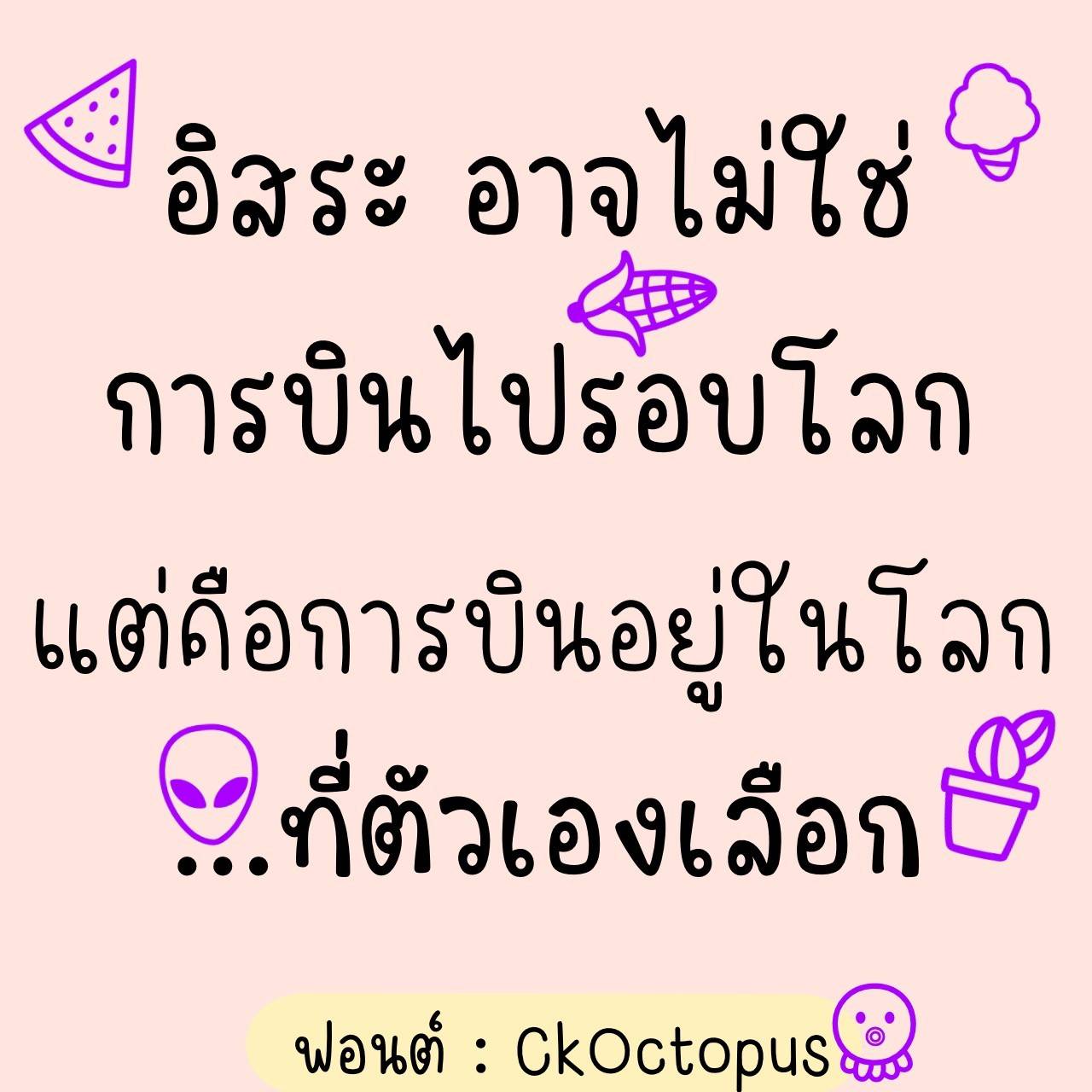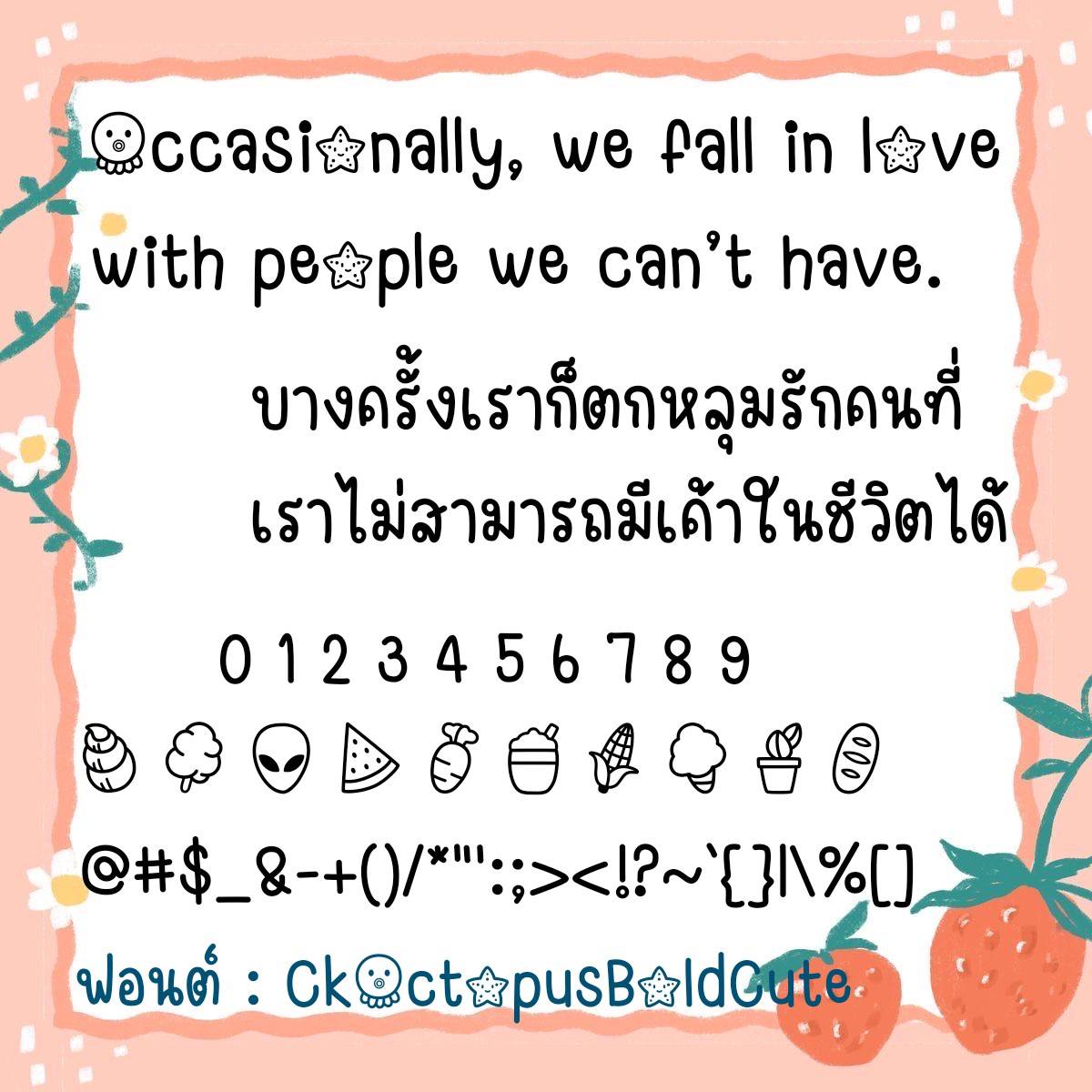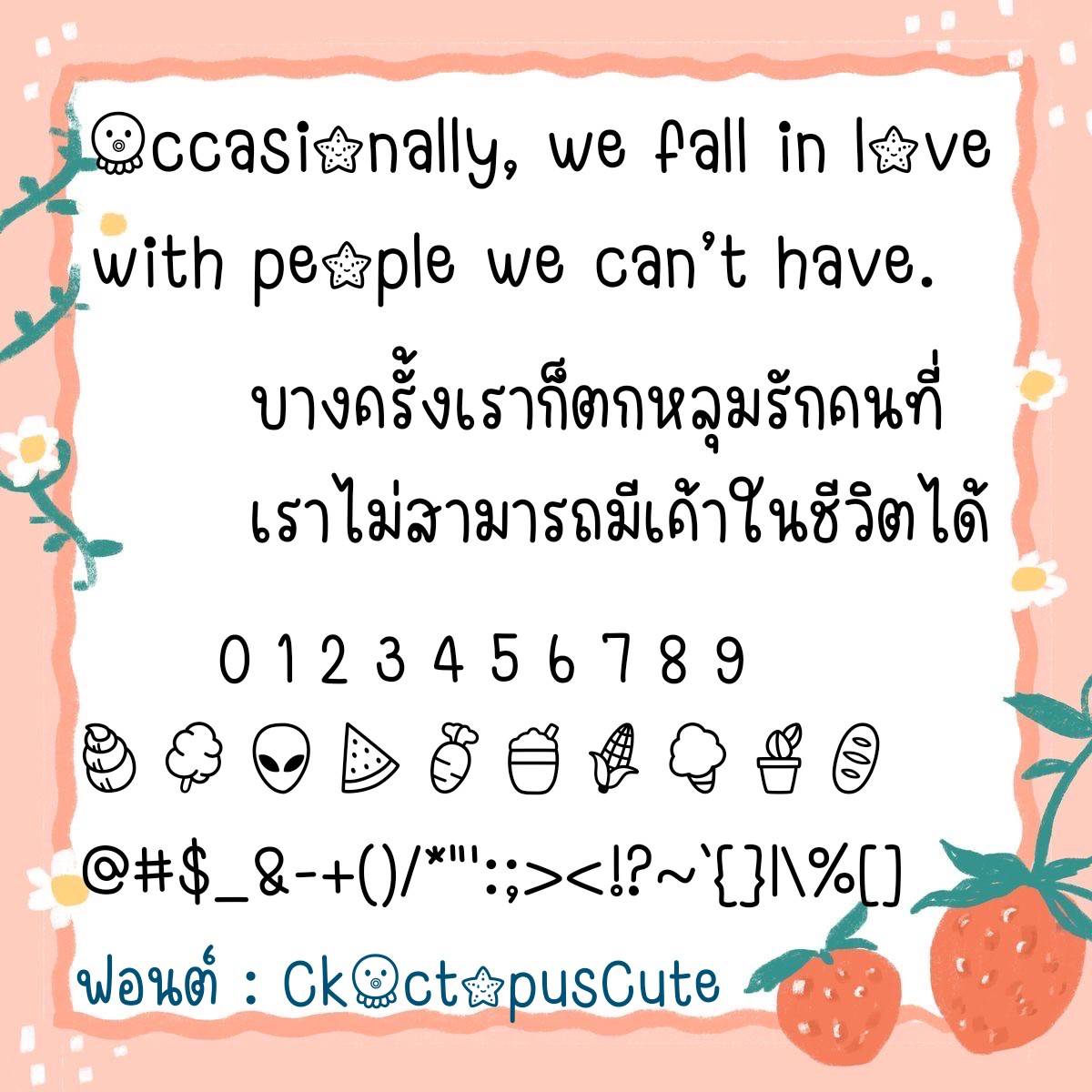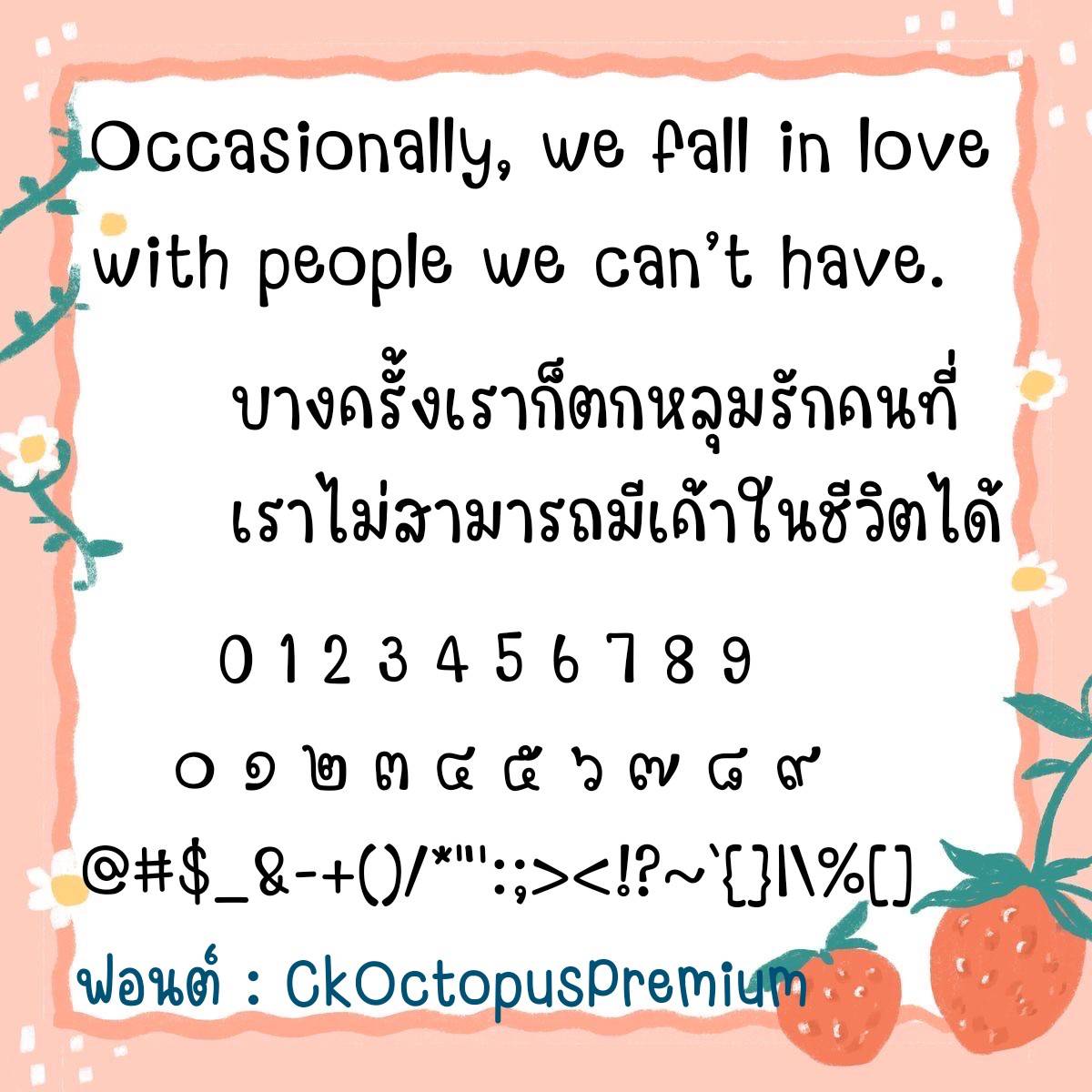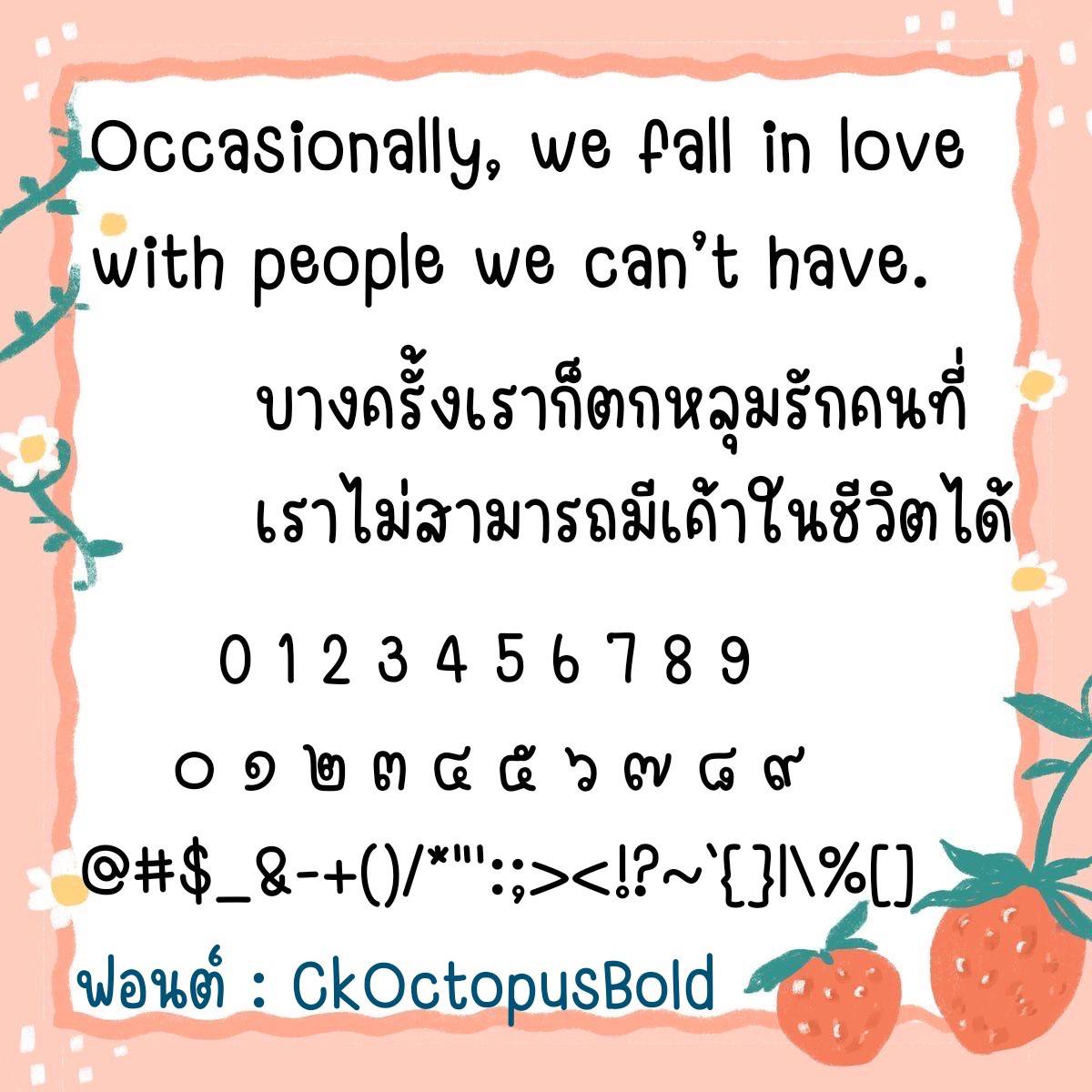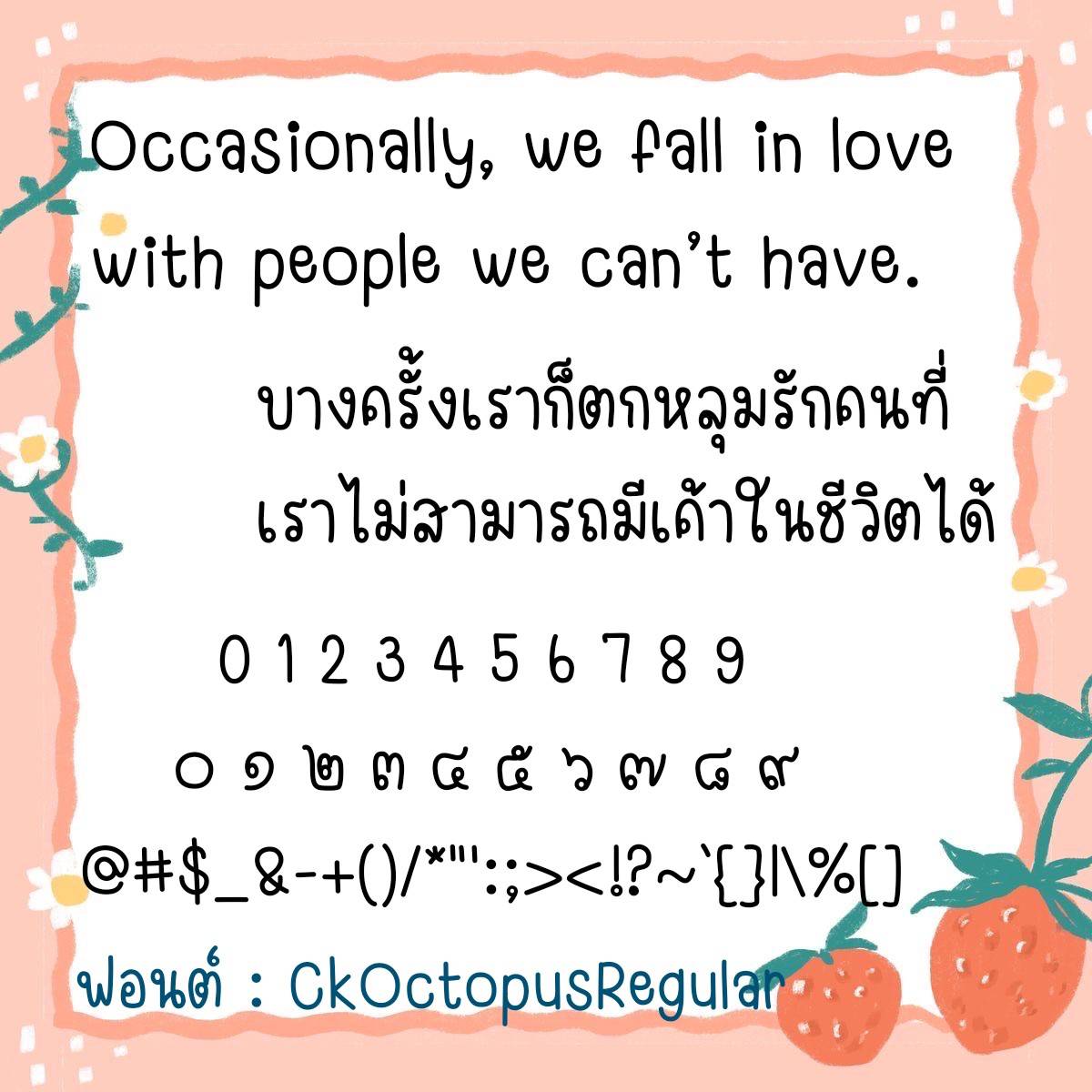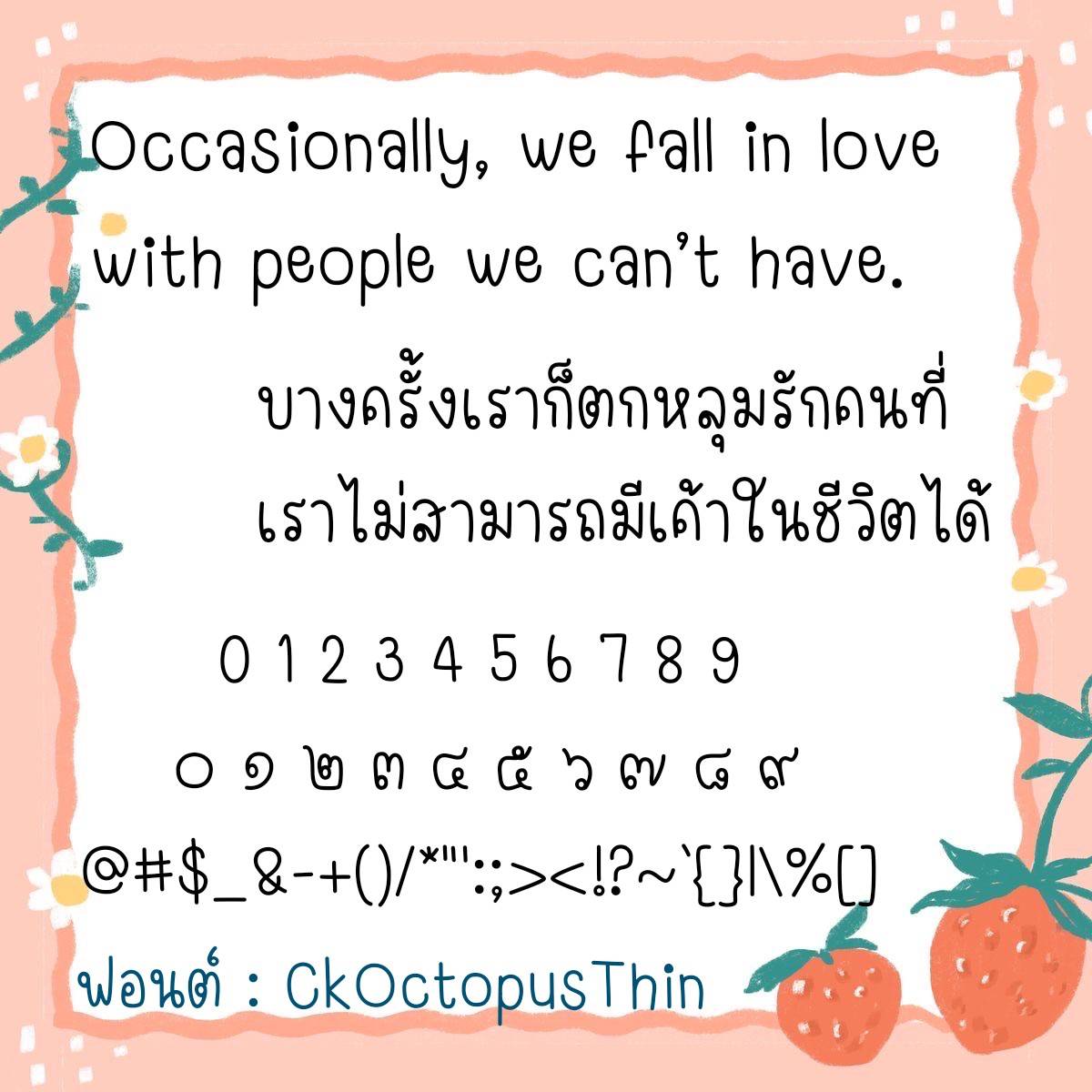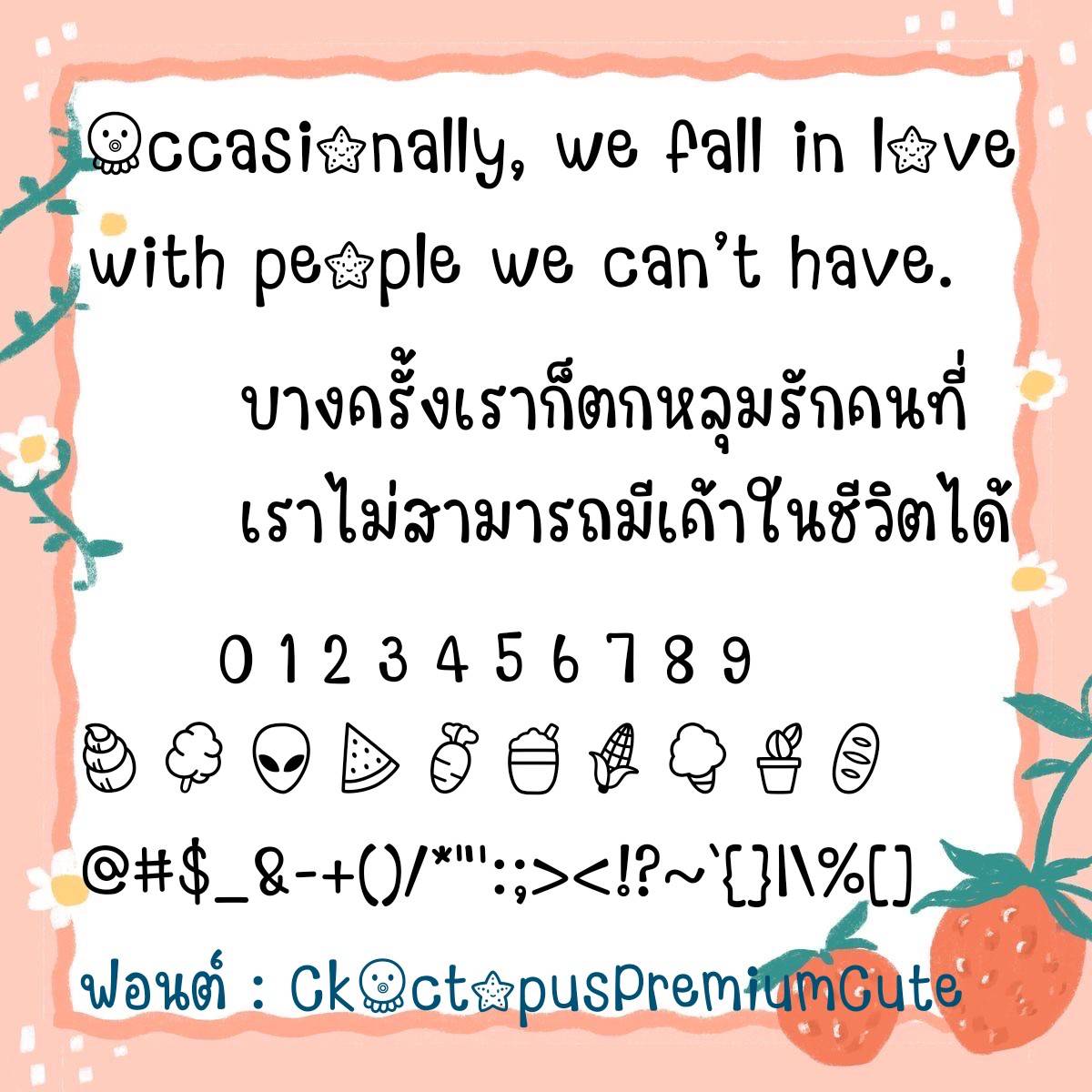
Font CkOctopus
🔸ฟอนต์ลายมือแนวกึ่งวัยรุ่น เขียนหวัดนิดๆ ฟอนต์มีความน่ารัก ตัวอ้วนอ่านง่าย และยังมีไฟล์อิโมจิน่ารักๆที่ใช้แทนเลขไทยให้ในชุดด้วยค่ะ 🥰💙
🔹A semi-teenage handwritten font with a little cursive writing. The font is cute, chubby and easy to read. There is also a cute emoji file that can be used to replace Thai numerals in the set.🥰💙